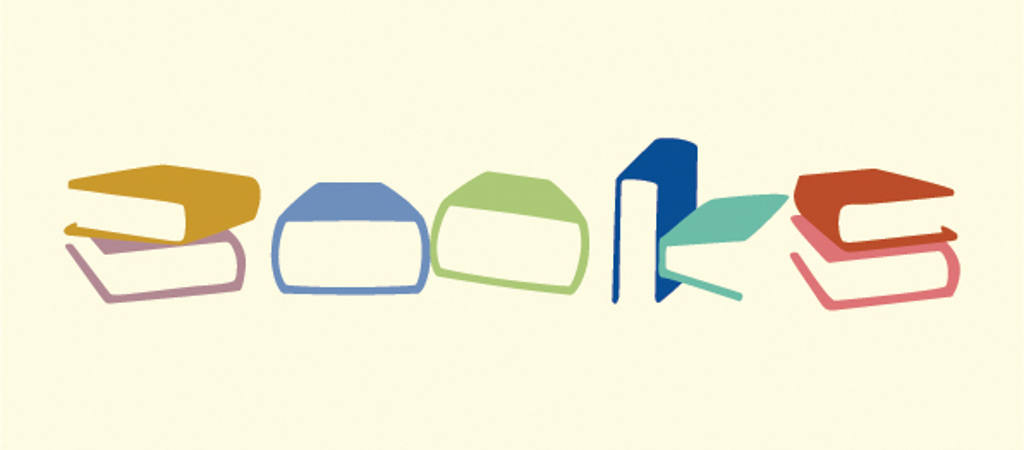
Ötletes tipográfiai megoldás ez a könyvekből kirakott "books" felirat.
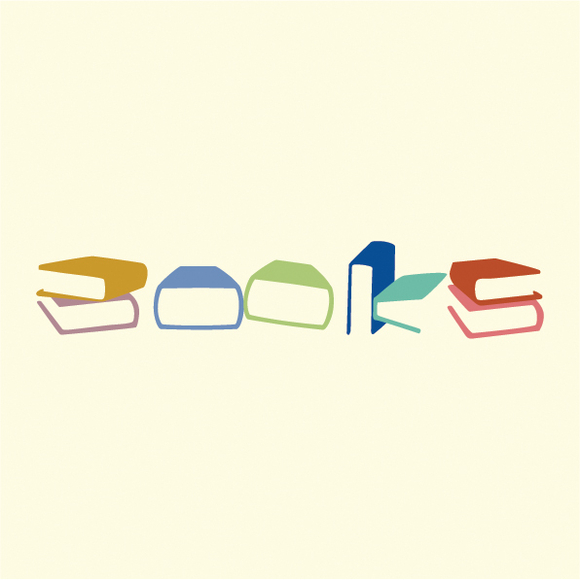
Ötletes tipográfiai megoldás ez a könyvekből kirakott "books" felirat. A grafikus máshogy fogta meg a "könyvekből betűt" koncepciót.